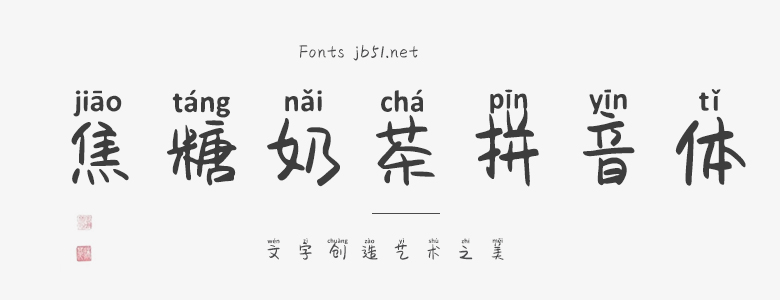
焦糖奶茶拼音體是一款獨具匠心的字體設(shè)計,其靈感來源于焦糖奶茶的獨特韻味和魅力。字體線條流暢、優(yōu)雅,仿佛在紙上流動的焦糖奶茶,絲絲入扣,令人陶醉。 焦糖奶茶拼音體的字母形狀獨特,每個字母都有自己獨特的細節(jié)和特點。比如字母“a”的頂部就像奶茶中的泡泡,而“o”的形狀則像一顆珍珠,令人想到焦糖奶茶中的珍珠口感。整個字體的設(shè)計都充滿了細節(jié)和趣味性,讓人在使用時感到愉悅和驚喜。 此外,焦糖奶茶拼音體的字體間距和字重也經(jīng)過了精心的調(diào)整,使字體在各種場合都能夠呈現(xiàn)出最佳的視覺效果。無論是用于書寫文本還是作為裝飾元素使用,焦糖奶茶拼音體都能夠為用戶帶來一種溫馨、甜美的感覺,仿佛每一句話都融入了焦糖奶茶的香氣和滋味。 總的來說,焦糖奶茶拼音體是一款充滿創(chuàng)意和趣味性的字體設(shè)計,它將漢字的優(yōu)美與焦糖奶茶的獨特韻味完美結(jié)合,為用戶帶來一種全新的視覺體驗。無論是在閱讀還是在創(chuàng)作中,焦糖奶茶拼音體都將讓你的文字更加生動、有趣,讓你沉浸在字體的魅力之中。